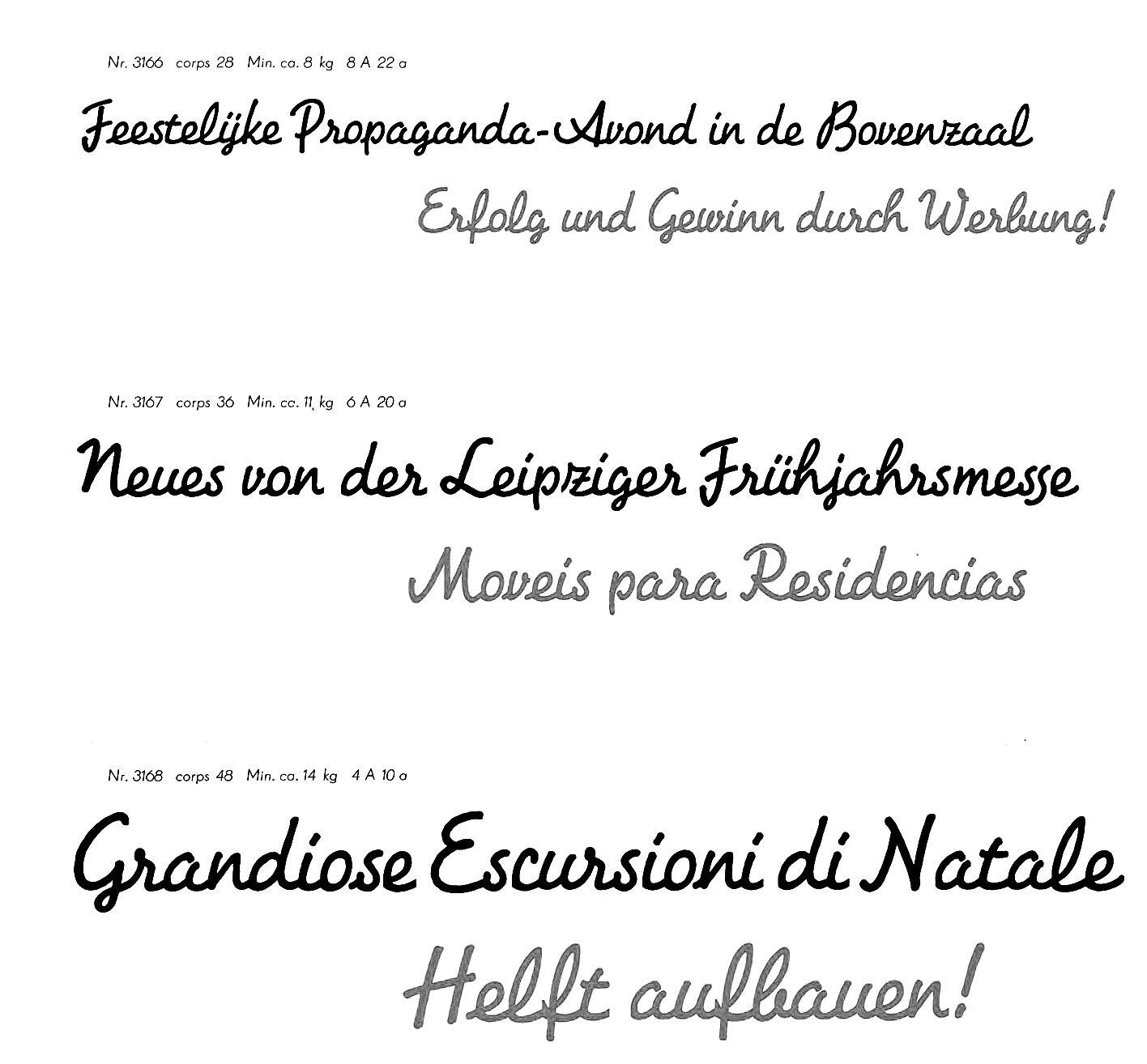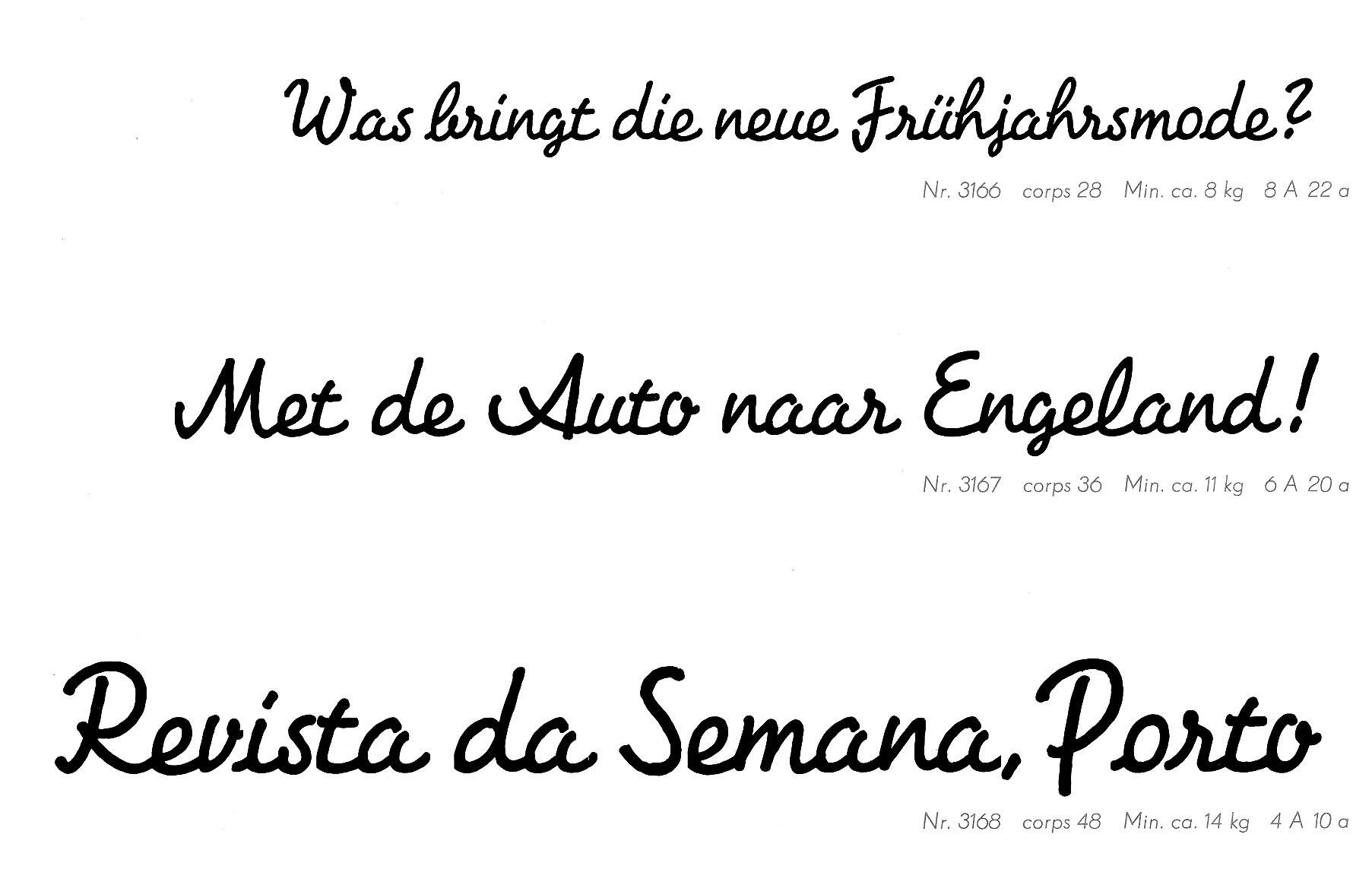
Die Appell ist eine verbundene Werbeschreibschrift von Arno Drescher und erschien 1933 über Schriftguss. Die Schrift ist eine leichte Variante zur zuvor erschienenen Energos, bekam jedoch einen eigenen Namen.